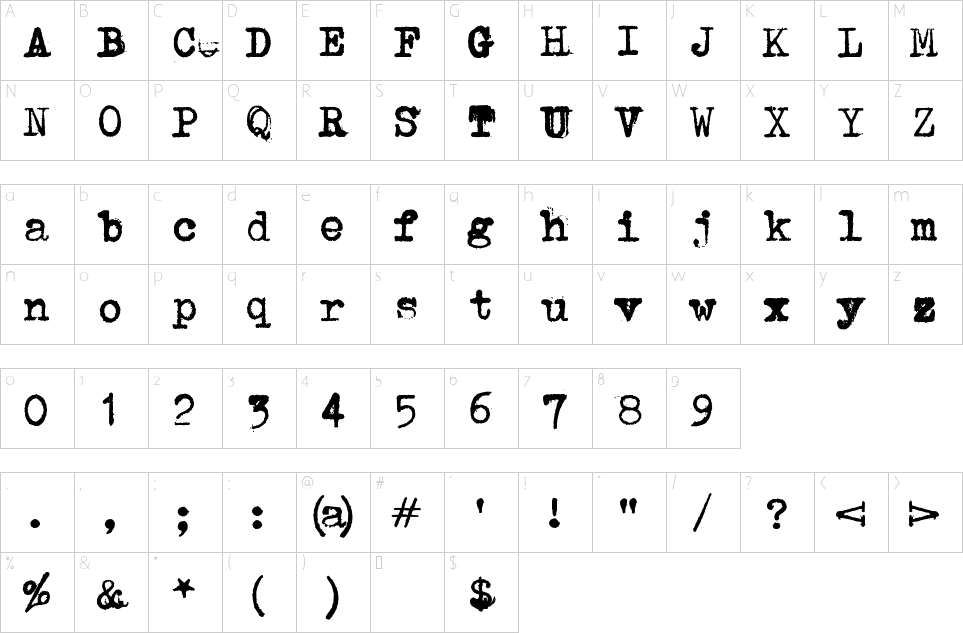
Descubra uma fonte gratuita e elegante chamada Avojaloin. Esta font foi projetada por junkohanhero e já foi baixada mais de 9.766 vezes. Avojaloin combina sofisticação e simplicidade, adequada para uma ampla variedade de projetos de design gráfico. Seja para criar um layout de jornal, estilizar uma logomarca ou decorar um poster, Avojaloin estará sempre à mão. Baixe a font e experimente os inúmeros benefícios que ela oferece.